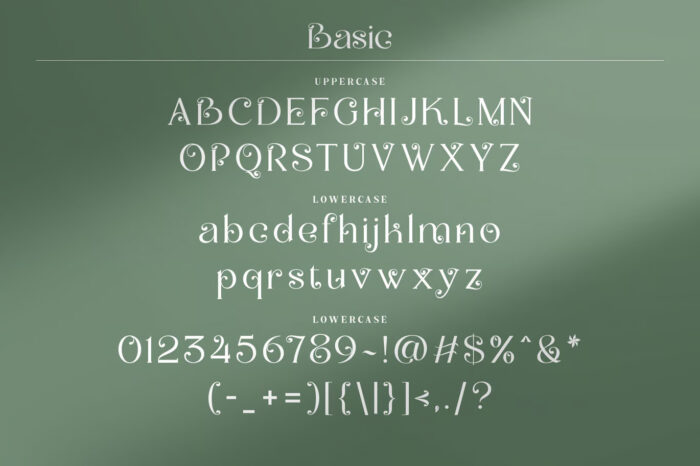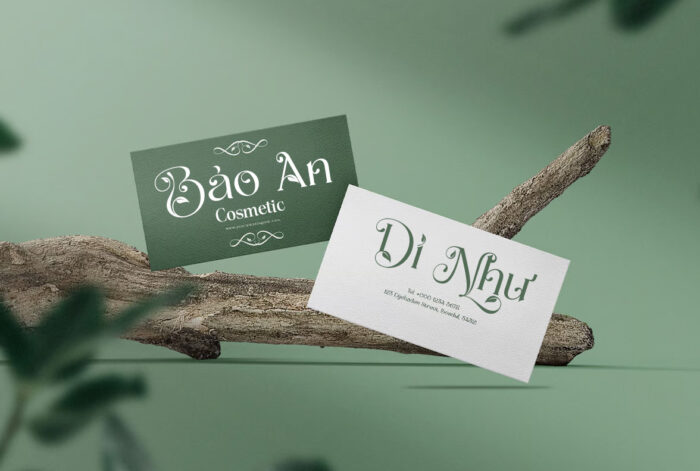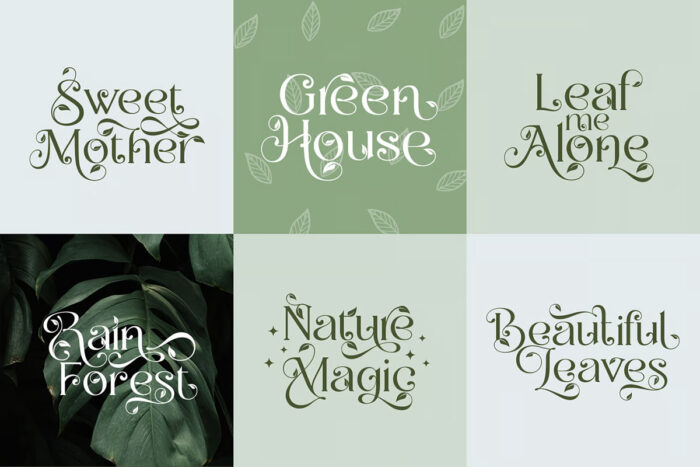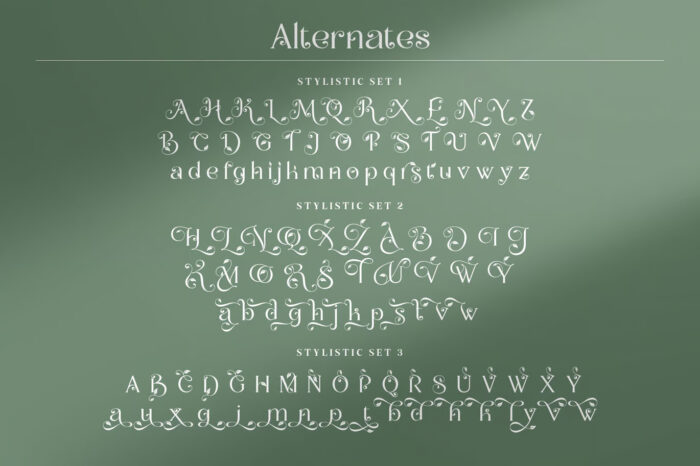
DVN Flora – Font tạo hình lá cây tuyệt đẹp phù hợp với thương hiệu thiên nhiên, Cosmetic, mỹ phẩm
DVN Flora là một font chữ sáng tạo được thiết kế với cảm hứng từ thiên nhiên. Các ký tự được tạo hình tỉ mỉ với những chi tiết mềm mại như lá cây, mang lại cảm giác thanh thoát và dịu nhẹ. Font này không chỉ tạo ấn tượng mạnh mẽ về mặt thị giác mà còn thể hiện sự tinh tế, hoàn hảo cho các thương hiệu liên quan đến thiên nhiên, mỹ phẩm, và các sản phẩm chăm sóc sắc đẹp. Với phong cách trang nhã và hiện đại, DVN Flora giúp thương hiệu của bạn nổi bật với vẻ ngoài thân thiện, gắn kết với môi trường. Đây chắc chắn là sự lựa chọn tuyệt vời cho logo, bao bì sản phẩm hoặc các chiến dịch quảng cáo cần sự sang trọng và tươi mới.
Font có hỗ trợ Ligature và Glyphs giúp bạn tạo ra hiệu ứng chữ hoa lá, xem hướng dẫn dùng Ligature và Glyphs tại đây
Ngoài ra bạn cũng có thể kích hoạt “stylistic alternates” để gõ chữ tự động ra lá trong Photoshop.